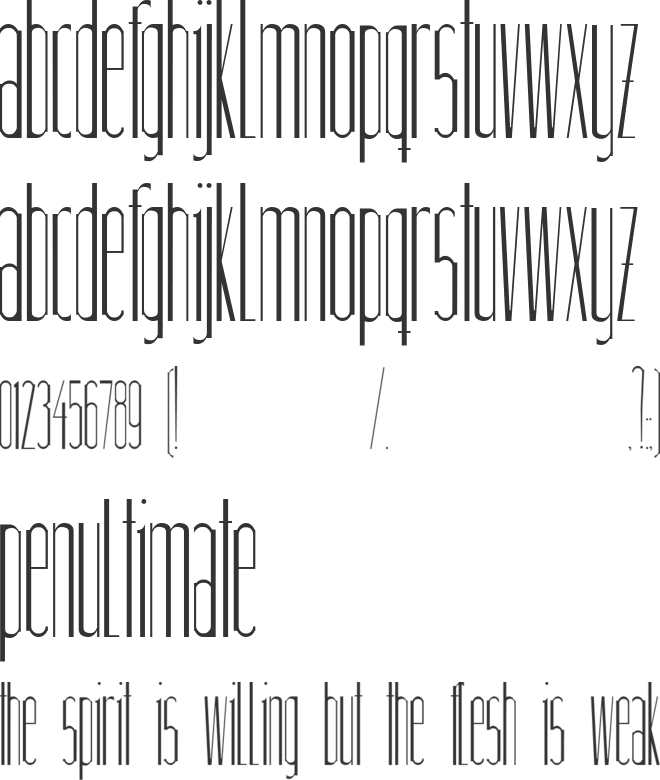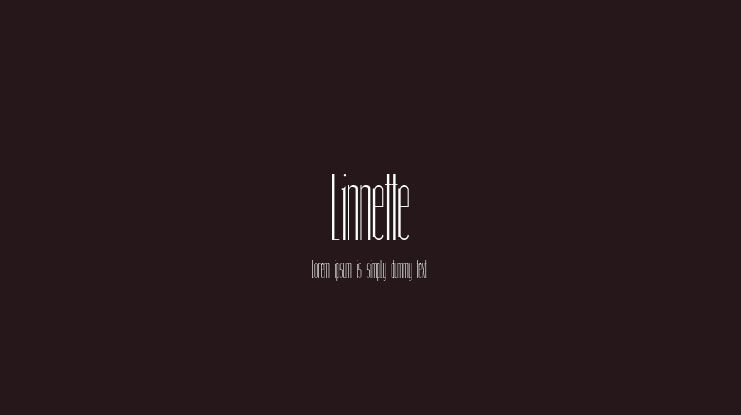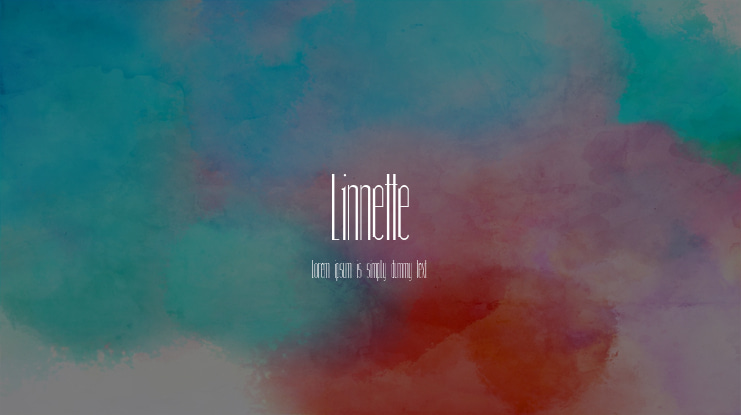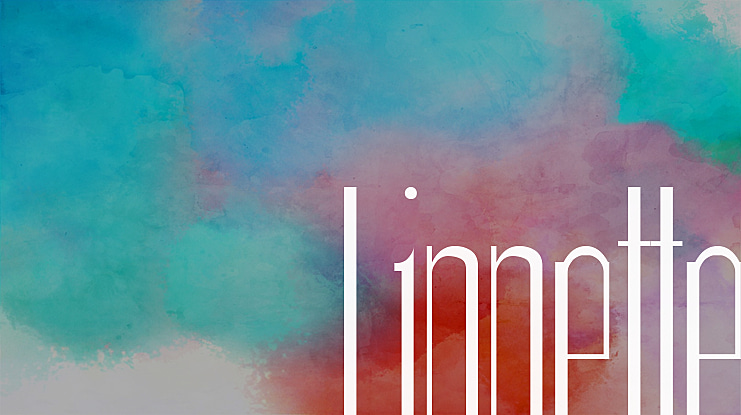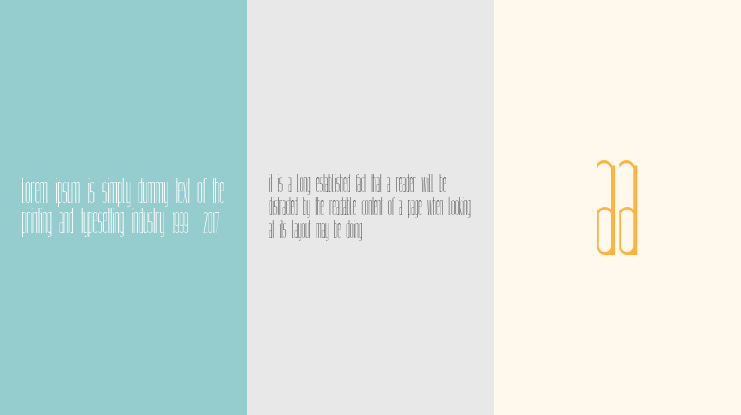
linnette Font
Linnette, está basada en la tipografía teatral de Jules Cheret, quería conseguir ese aire de cabaret modernista pero estilizando al máximo sus lineas. Es una tipografía de aire romántico que debe su nombre a su rasgo más evidente; la línea.